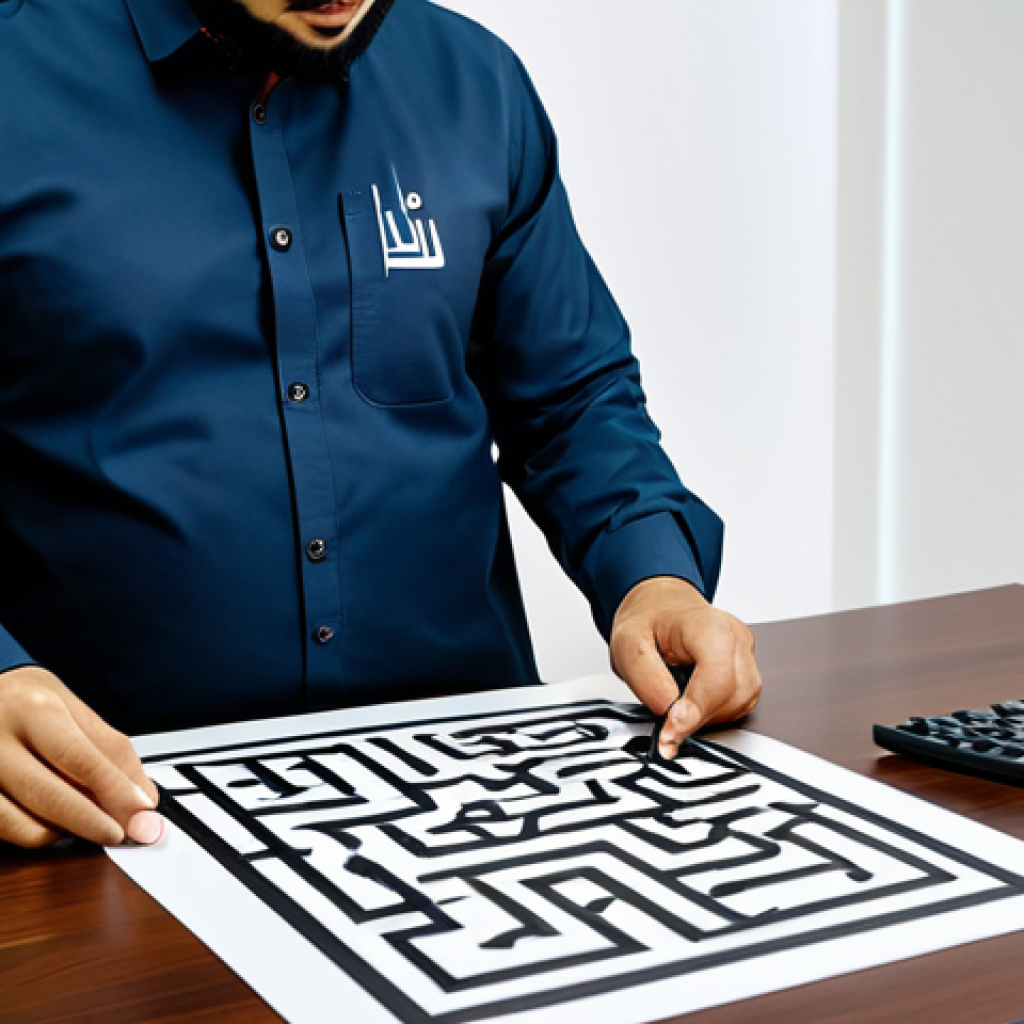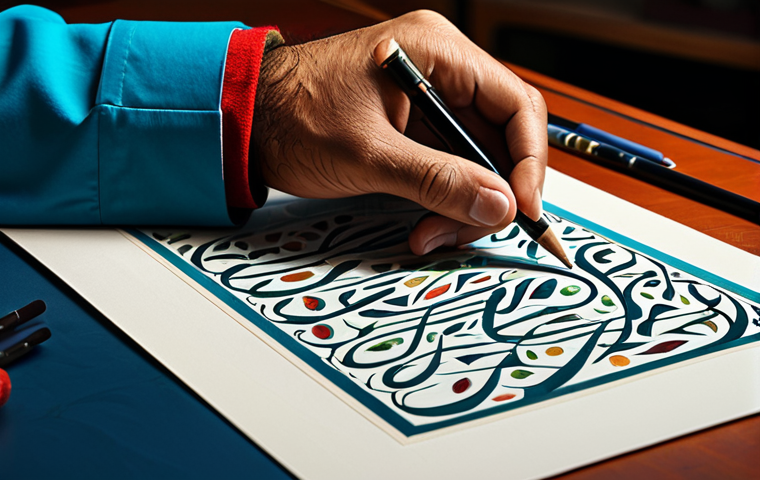
أنواع الخط العربي: دليل شامل لتوفير المال واختيار الأنسب لتصميماتك
الخطوط العربية، تلك اللوحة الفنية التي تزين صفحات الكتب والمواقع الإلكترونية، ليست مجرد وسيلة لنقل الكلمات، بل هي تعبير عن ثقافة عريقة وتاريخ طويل. لكل خط عربي جماله الخاص وقدرته على إضفاء طابع فريد على النص.
من الخط الكوفي الهندسي الصارم إلى خط النسخ الأنيق، تتنوع الخطوط العربية لتناسب مختلف الأذواق والاستخدامات. شخصياً، أجد في خط الثلث سحراً خاصاً، فهو يجمع بين القوة والمرونة، ويعكس جمالية الخط العربي الأصيل.
في السنوات الأخيرة، شهدنا تطوراً ملحوظاً في الخطوط العربية الرقمية، مما أتاح لنا استخدامها بسهولة في التصميم والطباعة. هذا التطور يتماشى مع التوجهات الحديثة في عالم التكنولوجيا، حيث يسعى المصممون إلى إبراز الهوية العربية في مختلف المشاريع.
ومن المتوقع أن نشهد في المستقبل المزيد من الابتكارات في هذا المجال، مع ظهور خطوط جديدة تجمع بين الأصالة والمعاصرة. دعونا نستكشف هذا العالم المدهش من الخطوط العربية بتفصيل أكبر!
جماليات الخط العربي وتأثيره على التصميم الحديث
الخط العربي ليس مجرد وسيلة للكتابة، بل هو فن له قواعده وجمالياته الخاصة. لقد تطور عبر العصور، ليشكل جزءاً لا يتجزأ من الثقافة العربية والإسلامية. في التصميم الحديث، يُستخدم الخط العربي لإضفاء لمسة من الأصالة والرقي على مختلف الأعمال، من تصميم الشعارات إلى تصميم المواقع الإلكترونية.
الخط الكوفي: رمز الأصالة والقوة
الخط الكوفي، بأشكاله الهندسية المميزة، يعتبر من أقدم الخطوط العربية وأكثرها استخداماً في الزخرفة المعمارية والنقوش الإسلامية. يتميز هذا الخط بقوته وثباته، ويعكس عظمة الحضارة الإسلامية.
في التصميم الحديث، يُستخدم الخط الكوفي لإضفاء طابع رسمي وجاد على التصميم، كما يمكن استخدامه في تصميم الشعارات التي تعبر عن الأصالة والتراث. أتذكر عندما زرت مسجد قرطبة في إسبانيا، اندهشت بجمال النقوش الكوفية التي تزين جدرانه، والتي تعكس عظمة الفن الإسلامي في تلك الحقبة.
خط النسخ: الأناقة والوضوح في الكتابة
خط النسخ هو الخط الأكثر استخداماً في طباعة الكتب والمجلات، وذلك بفضل وضوحه وسهولة قراءته. يتميز هذا الخط بأناقته وانسيابيته، مما يجعله مناسباً للاستخدام في مختلف أنواع النصوص.
في التصميم الحديث، يُستخدم خط النسخ في تصميم المواقع الإلكترونية والتطبيقات، حيث يضمن سهولة القراءة وتجربة مستخدم مريحة. شخصياً، أفضّل استخدام خط النسخ في كتابة الرسائل الإلكترونية والمستندات الرسمية، فهو يعكس الاحترافية والأناقة.
خط الرقعة: السرعة والعفوية في التعبير
خط الرقعة هو الخط الأكثر استخداماً في الكتابة اليومية، وذلك بفضل سرعته وسهولة كتابته. يتميز هذا الخط ببساطته وعفويته، مما يجعله مناسباً للاستخدام في كتابة الملاحظات والرسائل الشخصية.
في التصميم الحديث، يُستخدم خط الرقعة لإضفاء لمسة من المرح والعفوية على التصميم، كما يمكن استخدامه في تصميم الإعلانات والملصقات التي تستهدف الشباب. عندما كنت في الجامعة، كنت أستخدم خط الرقعة في كتابة ملاحظاتي الدراسية، فهو كان يساعدني على تدوين المعلومات بسرعة وسهولة.
تأثير الخط العربي على الهوية البصرية للعلامة التجارية
تعتبر الهوية البصرية للعلامة التجارية من أهم العناصر التي تميزها عن المنافسين. يمكن للخط العربي أن يلعب دوراً كبيراً في تعزيز الهوية البصرية للعلامة التجارية، وذلك من خلال استخدام خط مميز يعكس شخصية العلامة وقيمها.
اختيار الخط المناسب للعلامة التجارية
يعتمد اختيار الخط المناسب للعلامة التجارية على طبيعة العلامة والجمهور المستهدف. على سبيل المثال، إذا كانت العلامة التجارية تستهدف جمهوراً شاباً، فيمكن استخدام خط عصري وجريء.
أما إذا كانت العلامة التجارية تستهدف جمهوراً محافظاً، فيمكن استخدام خط كلاسيكي وأنيق. زرت مؤخراً شركة ناشئة متخصصة في صناعة القهوة، وقد اختاروا خطاً عربياً حديثاً لشعارهم، مما عكس حيوية العلامة التجارية وجاذبيتها للشباب.
استخدام الخط العربي في تصميم الشعار
يمكن استخدام الخط العربي في تصميم الشعار بطرق مختلفة، سواء من خلال كتابة اسم العلامة التجارية بالخط العربي، أو من خلال استخدام عناصر مستوحاة من الخط العربي في تصميم الشعار.
من المهم أن يكون الشعار بسيطاً وسهل التذكر، وأن يعكس شخصية العلامة التجارية. أتذكر شعار إحدى شركات الطيران الخليجية، والذي يجمع بين الخط العربي التقليدي والتصميم الحديث، مما يعكس هوية الشركة العربية والعالمية في آن واحد.
توحيد الخط المستخدم في جميع المواد التسويقية
من المهم توحيد الخط المستخدم في جميع المواد التسويقية للعلامة التجارية، من الموقع الإلكتروني إلى الإعلانات المطبوعة. هذا يساعد على بناء هوية بصرية قوية ومتسقة للعلامة التجارية.
أنصح دائماً الشركات بتطوير دليل للهوية البصرية، يحدد الخطوط والألوان المستخدمة في جميع المواد التسويقية، لضمان الاتساق والاحترافية.
الخط العربي في تصميم المواقع الإلكترونية والتطبيقات
تعتبر تجربة المستخدم من أهم العوامل التي تحدد نجاح الموقع الإلكتروني أو التطبيق. يمكن للخط العربي أن يلعب دوراً كبيراً في تحسين تجربة المستخدم، وذلك من خلال اختيار خط واضح وسهل القراءة، وتنسيق النصوص بشكل جيد.
اختيار الخط المناسب لواجهة المستخدم
يجب اختيار الخط المناسب لواجهة المستخدم بعناية، مع مراعاة حجم الخط والتباعد بين الأسطر. يجب أن يكون الخط واضحاً وسهل القراءة على مختلف الأجهزة، من الهواتف الذكية إلى أجهزة الكمبيوتر المكتبية.
ج3: من أبرز التحديات هي الحفاظ على جمالية الخط العربي الأصيل في البيئة الرقمية. فالخطوط الرقمية قد تفقد بعضاً من تفاصيلها الدقيقة عند عرضها على الشاشات.
بالإضافة إلى ذلك، هناك تحدي دعم اللغة العربية بشكل كامل في مختلف البرامج والتطبيقات، خاصة فيما يتعلق بالتشكيل والوصلات بين الحروف. شخصياً، أعتقد أن التغلب على هذه التحديات يتطلب تعاوناً وثيقاً بين مصممي الخطوط ومطوري البرمجيات لضمان تجربة مستخدم سلسة ومرضية.